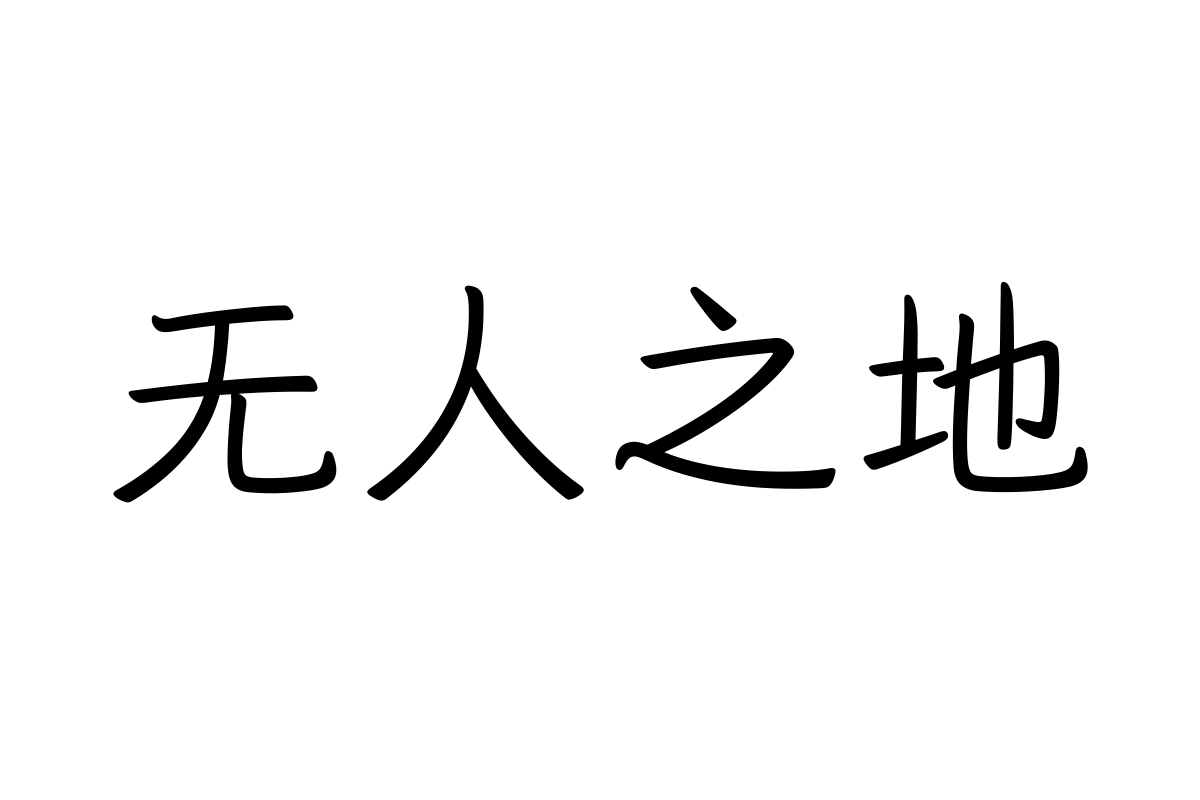
汉仪唐美人-45是一款具有独特美感的中文字体,它源自唐代的书法艺术,融合了现代审美和传统韵味。这款字体线条流畅,结构紧凑,给人以优雅、高贵的感觉。它的字形规整,笔画粗细适中,既有力度又不失柔和,适合用于标题、正文等多种场合。此外,汉仪唐美人-45还具有一定的可读性,既适合印刷也适合电子屏幕显示,是一款非常实用的字体。